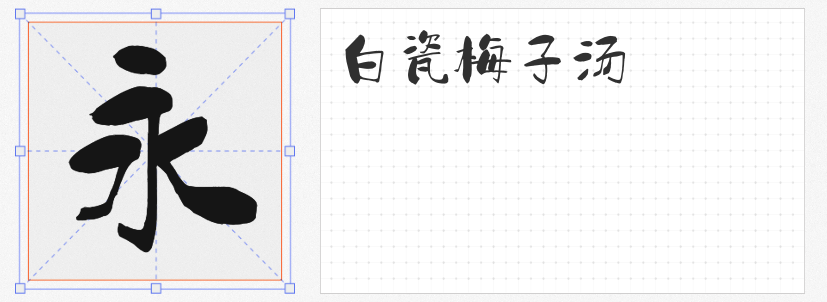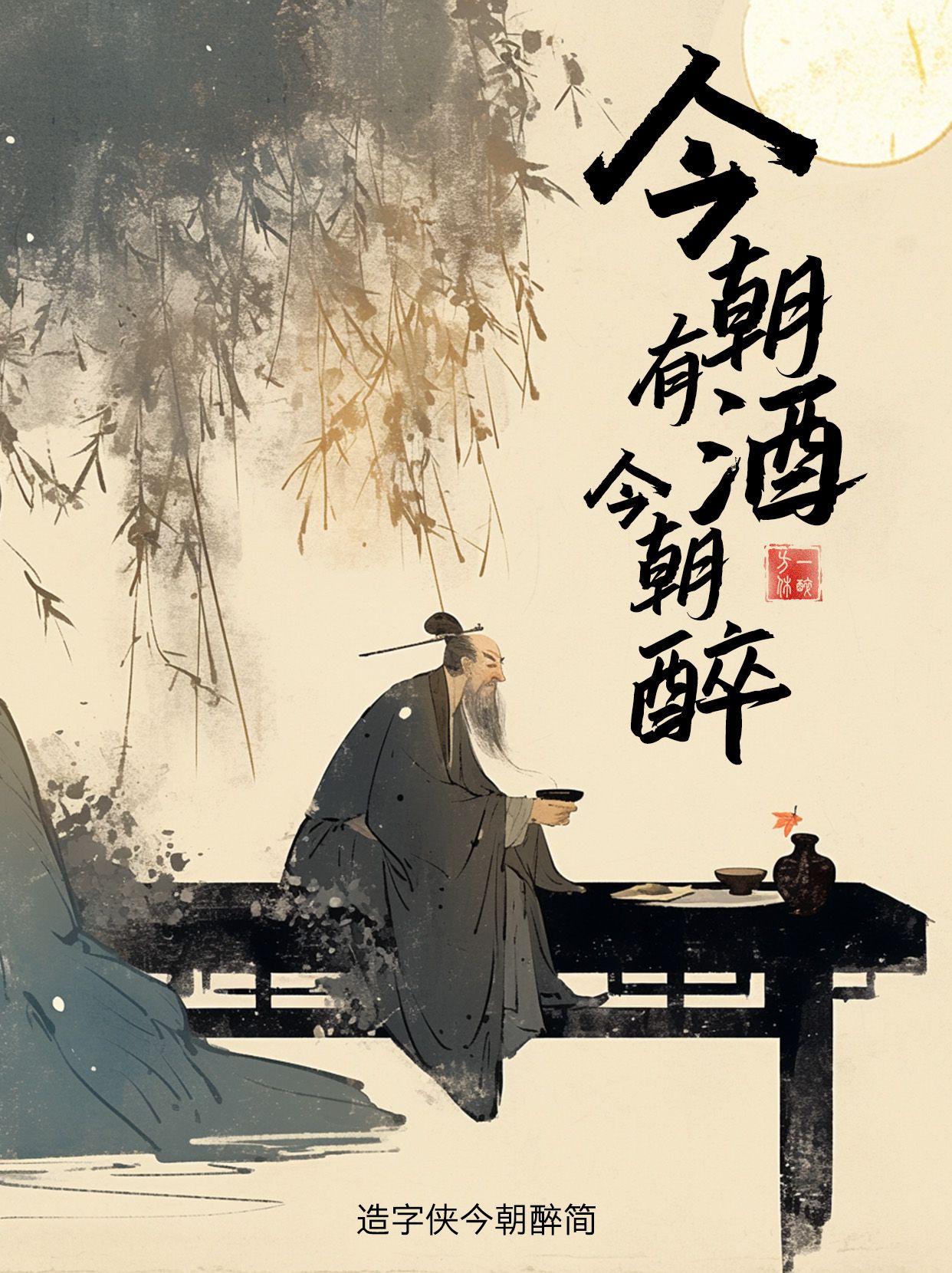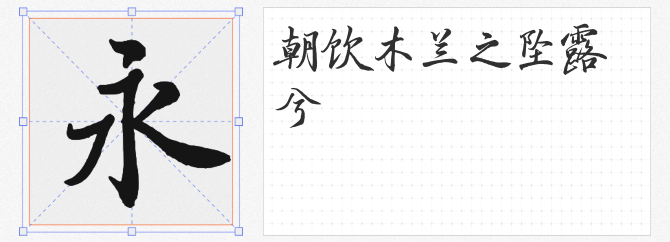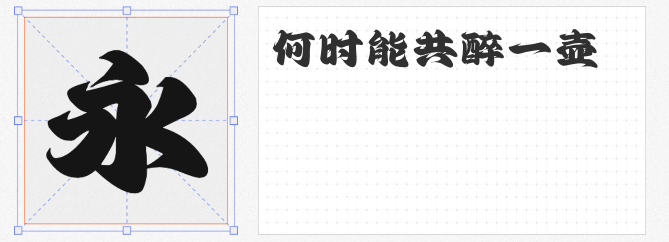
端午将至,粽香氤氲间,设计之美亦需以字传情。以下四款非免费但独具匠心的字体,恰能为端午主题设计注入文化底蕴与视觉张力,让传统与现代在笔墨间交融。
1. 云书法玉兰行楷体
这款毛笔字体以行楷为骨,刚柔并济。主笔画如龙舟破浪般挺拔,牵丝连带似粽叶飘逸,字形匀称中透出层次分明的块面感。无论是端午海报的磅礴标题,还是书籍封面的雅致题字,其灵动洒脱的笔触皆能烘托节日的热烈与诗意,让观者在墨香中感受千年文化的呼吸。
2. 龙书法勘亭流风
以“勘亭流体”为灵感,这款字体融合了古典的敦厚与现代的轻盈。圆润字形如饱满的粽子,布白饱满而富有张力,结体方正中透出宽博气度。在端午主题的海报、包装或短视频中,它既能传递龙舟竞渡的庄重感,又能以轻盈笔触呼应节日的欢愉,是传统工艺与现代设计碰撞的绝佳载体。
3. 万人字造昊仔体 大粗
一笔细横如粽叶轻拂,一笔厚竖似龙舟桅杆,万人字造昊仔体 大粗以高识别性的笔画和活泼的姿态脱颖而出。重心偏下的字形如孩童嬉戏般俏皮,却又不失平衡之美。在端午文创、儿童主题海报或短视频中,其自由灵动的风格能为传统注入青春气息,让节日氛围更显生动鲜活。
4. 造字侠今朝醉简
这款毛笔楷书以“醉”为魂,收笔如酒意酣畅,笔法雄浑洒脱。其劲健的笔触与端午“饮雄黄酒”的习俗暗合,尤其适合白酒包装或高端礼盒设计。当字体与酒器纹样相映成趣,既彰显传统工艺的厚重,又传递出“今朝醉”的洒脱情怀,为节日增添一抹豪迈风骨。
四款字体,或如龙舟竞渡般气势磅礴,或如粽香四溢般温润绵长,或如孩童嬉戏般灵动鲜活,或如美酒入喉般酣畅淋漓。它们不仅是文字的载体,更是端午文化的视觉诠释者。设计师可根据项目需求,择其一二,让笔墨与节日共鸣,让设计在传统与创新间绽放独特魅力。